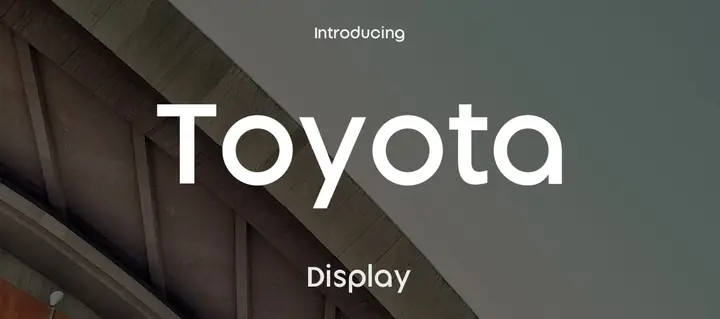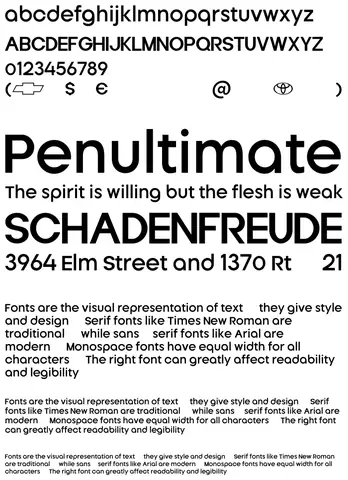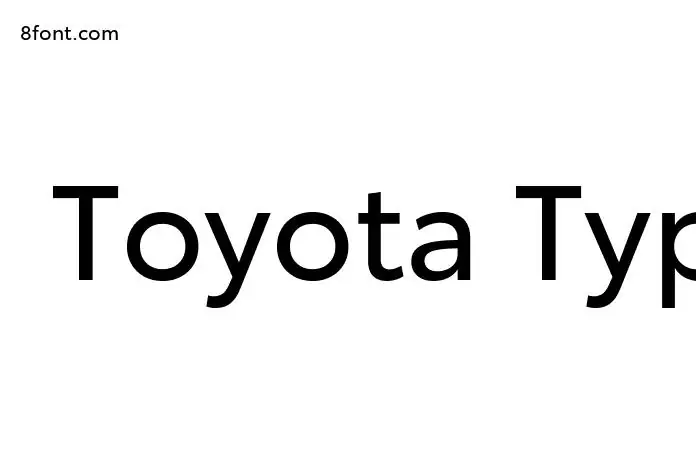
Mở đầu: Vì sao font “Toyota” lại được quan tâm?
Trong thế giới thiết kế đồ họa, việc lựa chọn một kiểu chữ (font) phù hợp không chỉ giúp tăng tính thẩm mỹ mà còn truyền tải đúng thông điệp thương hiệu. Đối với các nhà thiết kế, những người yêu thích ô tô, hoặc những fan hâm mộ của hãng Toyota, việc sở hữu font Toyota – một loại font mang đậm dấu ấn của thương hiệu – là một nhu cầu thiết yếu.
Font “Toyota” không chỉ là một bộ ký tự đơn thuần; nó là sự kết hợp giữa phong cách hiện đại, mạnh mẽ và tinh tế, phản ánh đúng tinh thần “Công nghệ tiên tiến, bền vững và đáng tin cậy” mà thương hiệu Toyota luôn hướng tới. Vì vậy, khi bạn tìm kiếm “toyota font download” trên các công cụ tìm kiếm, bạn thực sự đang tìm một công cụ mạnh mẽ để nâng tầm các dự án thiết kế của mình: từ poster quảng cáo, bìa sách, banner web, tới các mẫu in ấn khác.
1. Tổng quan về font Toyota: Đặc điểm và lịch sử phát triển
1.1. Nguồn gốc và ý nghĩa
• Nguồn gốc: Font Toyota được thiết kế nội bộ bởi bộ phận Marketing và Branding của Toyota Japan vào đầu những năm 2000, nhằm tạo nên một diện mạo đồng nhất cho tất cả các tài liệu truyền thông của hãng.
• Ý nghĩa: Các đường nét của font này được xây dựng dựa trên các yếu tố “độ bền” và “độ chính xác” – hai giá trị cốt lõi của Toyota. Đường thẳng và góc cạnh nhẹ nhàng tượng trưng cho sự ổn định, trong khi các vòng tròn mềm mại thể hiện tính linh hoạt và hiện đại.
1.2. Kiểu dáng và các biến thể
Font Toyota thường xuất hiện dưới ba dạng chính:
Biến thểĐặc điểmỨng dụng thường gặp
Toyota RegularĐường nét cân bằng, không quá dày, không quá mỏngVăn bản chính, tiêu đề phụ
Toyota BoldĐộ dày tăng lên 30%, tạo cảm giác mạnh mẽTiêu đề lớn, logo, quảng cáo
Toyota ItalicĐược nghiêng nhẹ, phù hợp cho chú thích, taglineTagline, slogan, các yếu tố phụ
Mỗi biến thể đều được thiết kế để hoạt động tốt trong cả môi trường in ấn và kỹ thuật số (web, ứng dụng di động).
Với những kiến thức và hướng dẫn chi tiết trên, bạn hiện đã sẵn sàng khai thác sức mạnh của Toyota Font trong mọi dự án sáng tạo – từ poster quảng cáo, brochure sản phẩm, cho tới giao diện website và video marketing. Hãy để chữ “Toyota” không chỉ là một ký tự, mà còn là biểu tượng của độ tin cậy, công nghệ và sự bền bỉ mà mọi người luôn mong muốn.